Как создать привлекательный текст с помощью шрифтов в Photoshop
Шрифты играют важную роль в создании графического дизайна. В Photoshop вы можете выбрать из огромного количества шрифтов, чтобы придать своим проектам уникальный вид и выразительность. В этой статье мы расскажем вам, как выбрать и использовать шрифты в Photoshop, чтобы создать убедительный дизайн.
Изучите разные стили шрифтов: жирные, курсивные, пропорциональные. Это поможет вам найти подходящий стиль для вашего проекта.
Учитывайте контекст использования шрифта. Разные шрифты могут быть подходящими для разных задач - некоторые лучше подходят для заголовков, а другие лучше для тела текста.
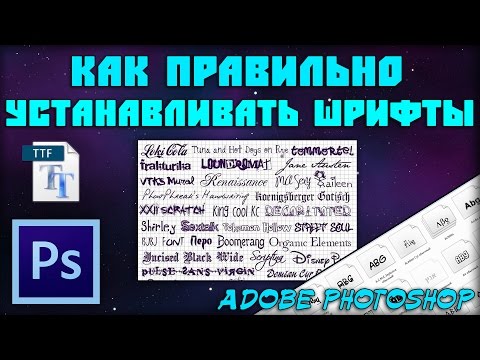
Не бойтесь экспериментировать с размером и весом шрифта. Перебирайте различные варианты, пока не найдете идеальный.